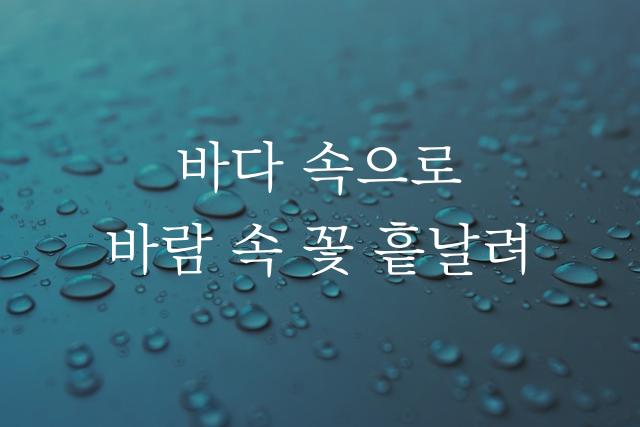
제주고딕은 제주도청에서 제작한 문서용 기본 고딕 폰트로, 꽉 찬 문자 구조가 특징입니다. 간결하면서도 독특한 개성을 가진 폰트로 다양한 문서에서 활용하기 좋습니다.
기본 고딕, 굵은 고딕, 감성적인, 단단함, 부드러움 계열의 생김새를 가지고 있으며
웹/앱 디자인, 보고서/문서, 출판물 제목 등에서 자주 활용되며, 효과적인 메시지 전달에 적합합니다.
이 폰트는 기술/IT, 관광/여행, 금융/비즈니스 분야에 잘 어울리며,
명확한, 전문적인, 단순한 느낌을 담고 있는 것이 특징입니다.